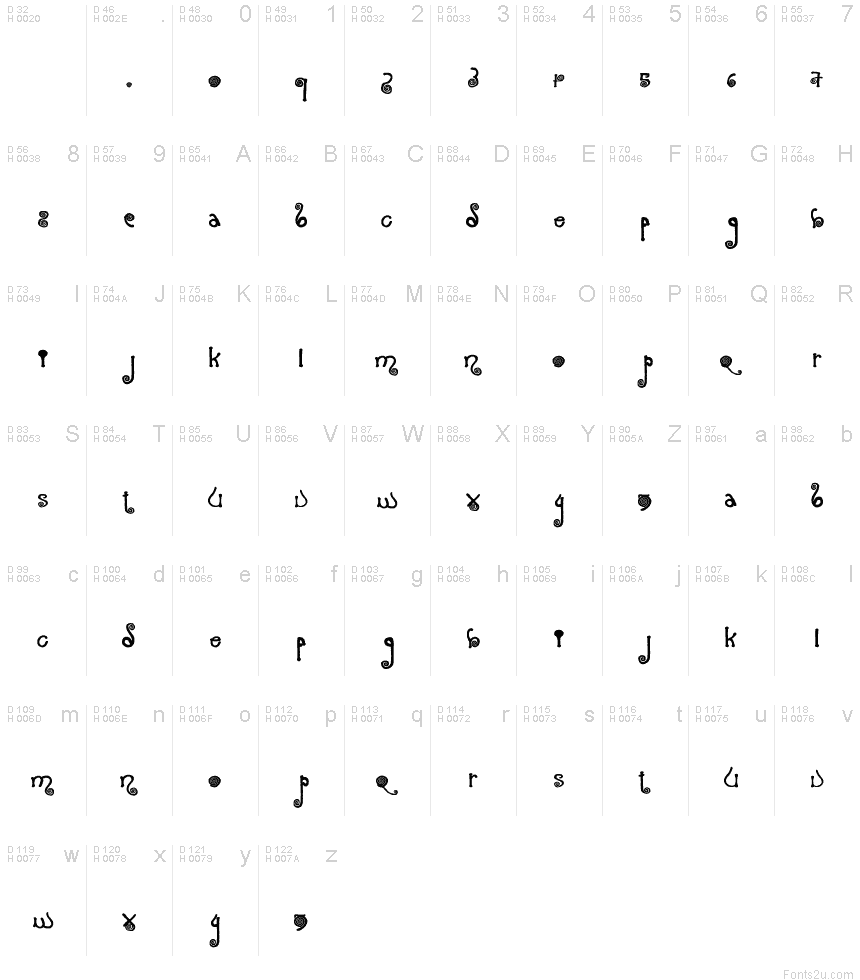
Spiraling autorstwa Chrisa Hansena to darmowy, kręcony krój typu display o luźnej dynamice pisma odręcznego. Jego zaokrąglone pociągnięcia rozszerzają się w bulwiaste zakończenia, a powtarzające się loczki do wewnątrz nadają literom żartobliwą, nieco dziwaczną sylwetkę. Nierówne wysokości i zmieniające się szerokości sprawiają, że formy są żywe, a nie mechanicznie powtarzalne.
Może służyć jako ilustrowany napis w książkach i grach dla dzieci. Spirale pasują do plakatów komediowych, opakowań słodyczy i rzemieślniczego brandingu dla młodszych odbiorców, gdzie litery mogą przywodzić na myśl lizaki, pnącza lub bazgrołowe stworki, zamiast służyć jedynie jako zwykły, neutralny krój pisma.